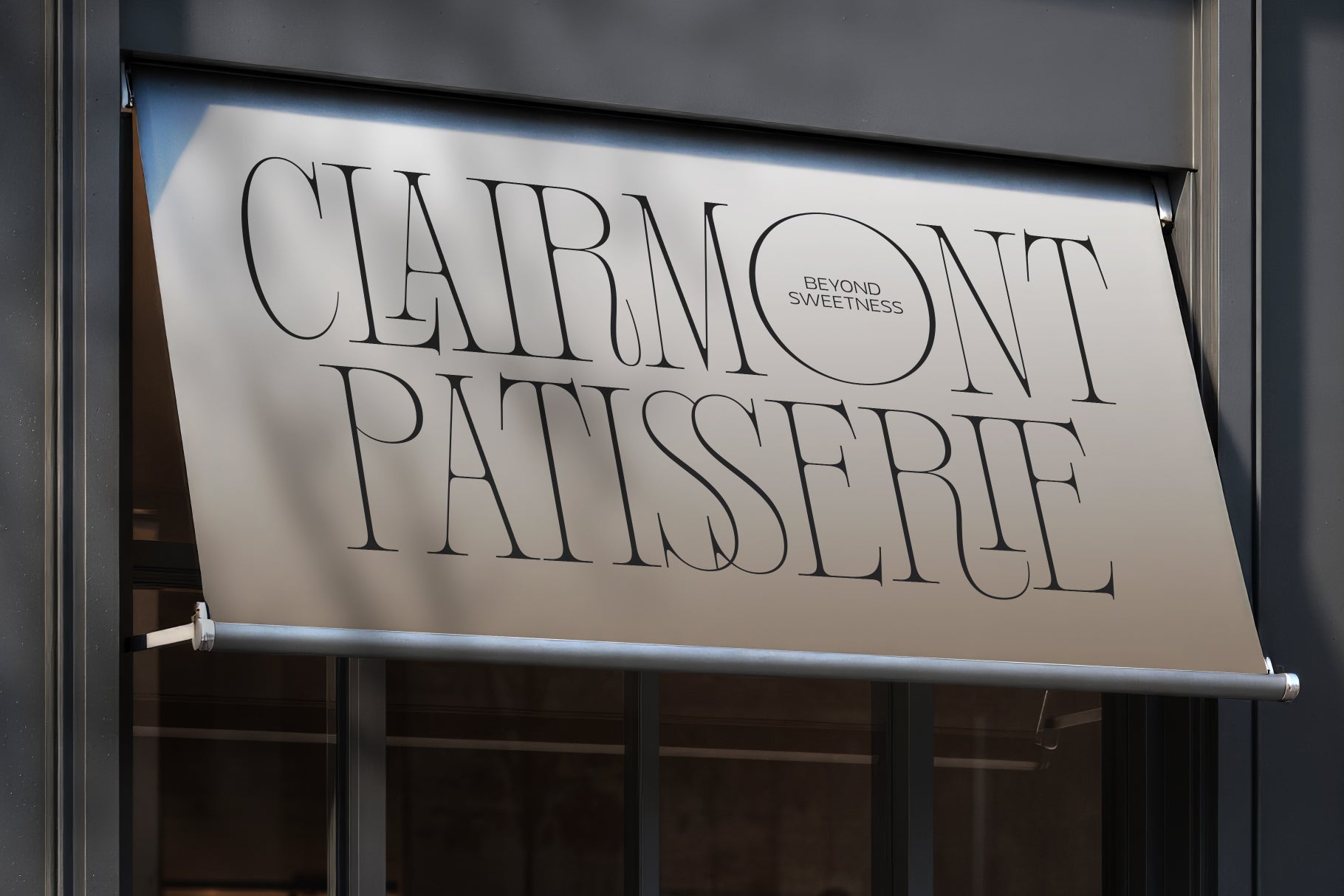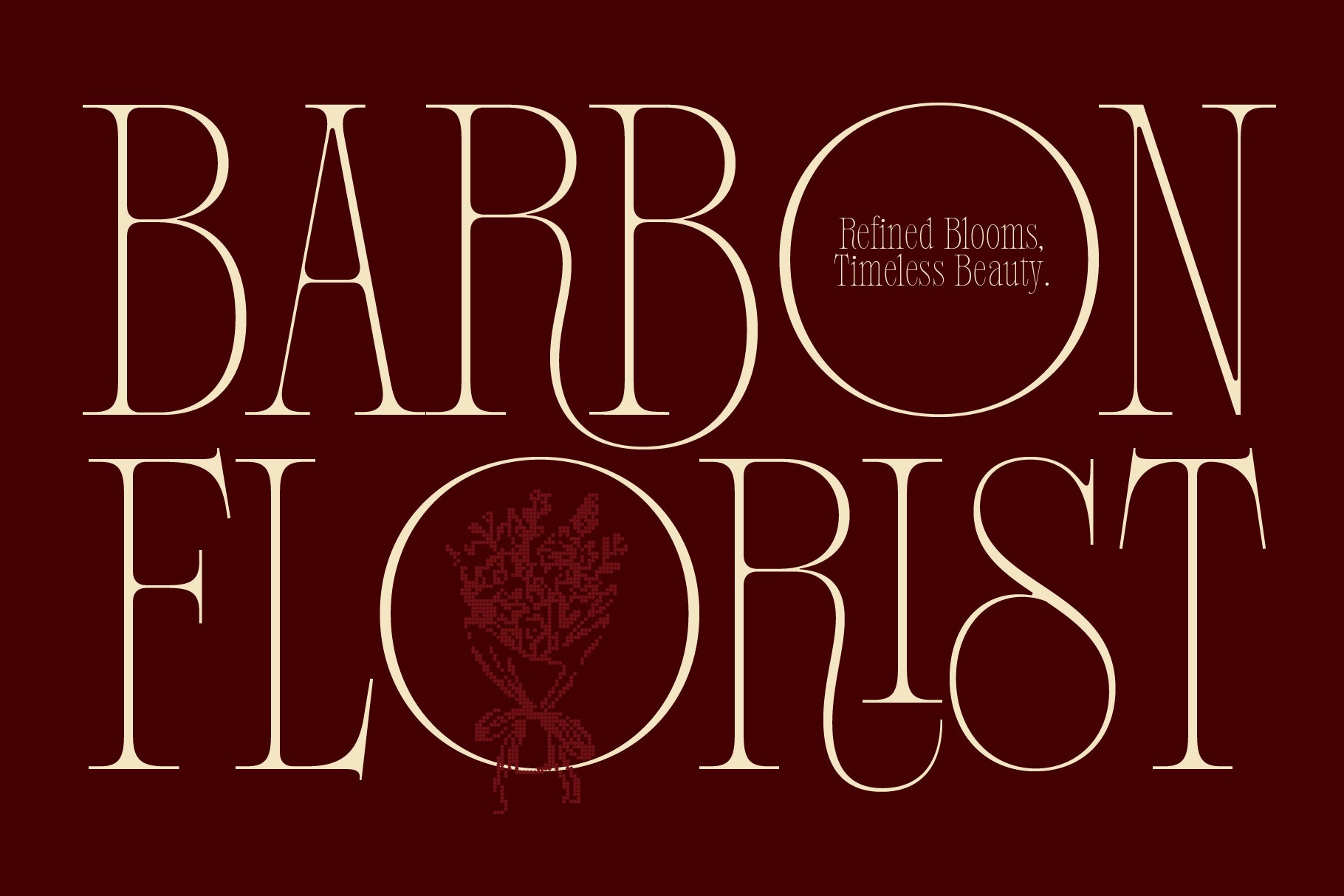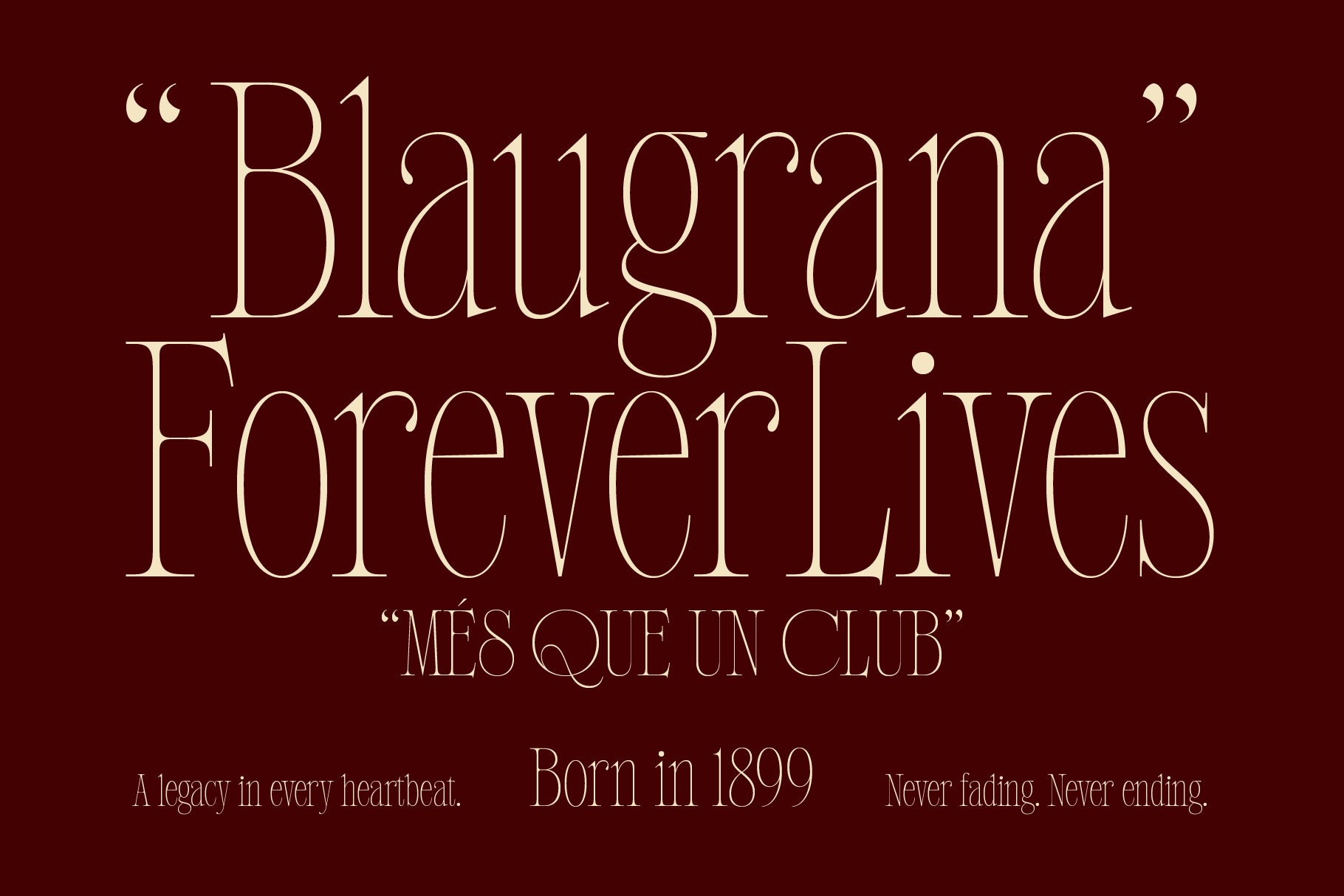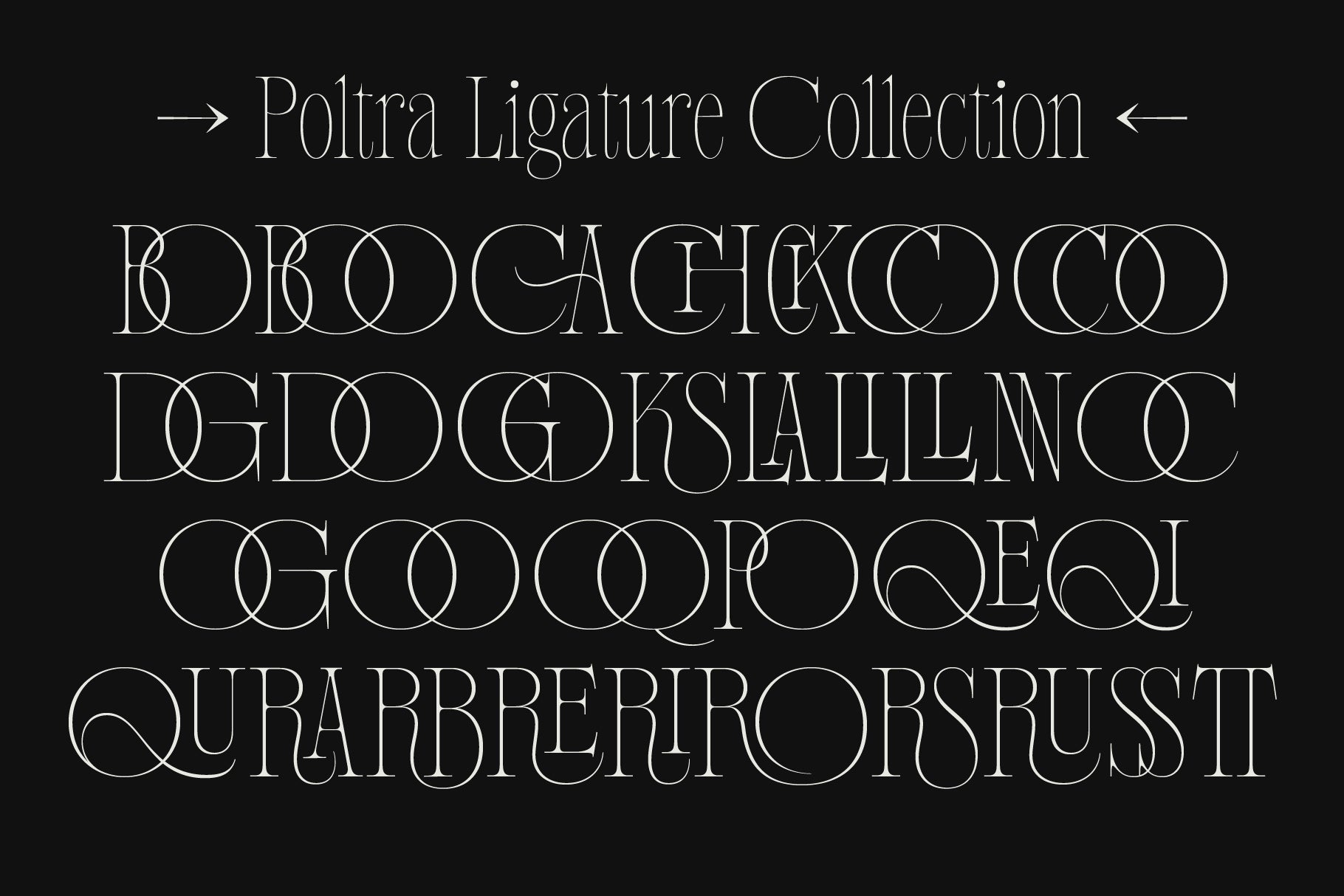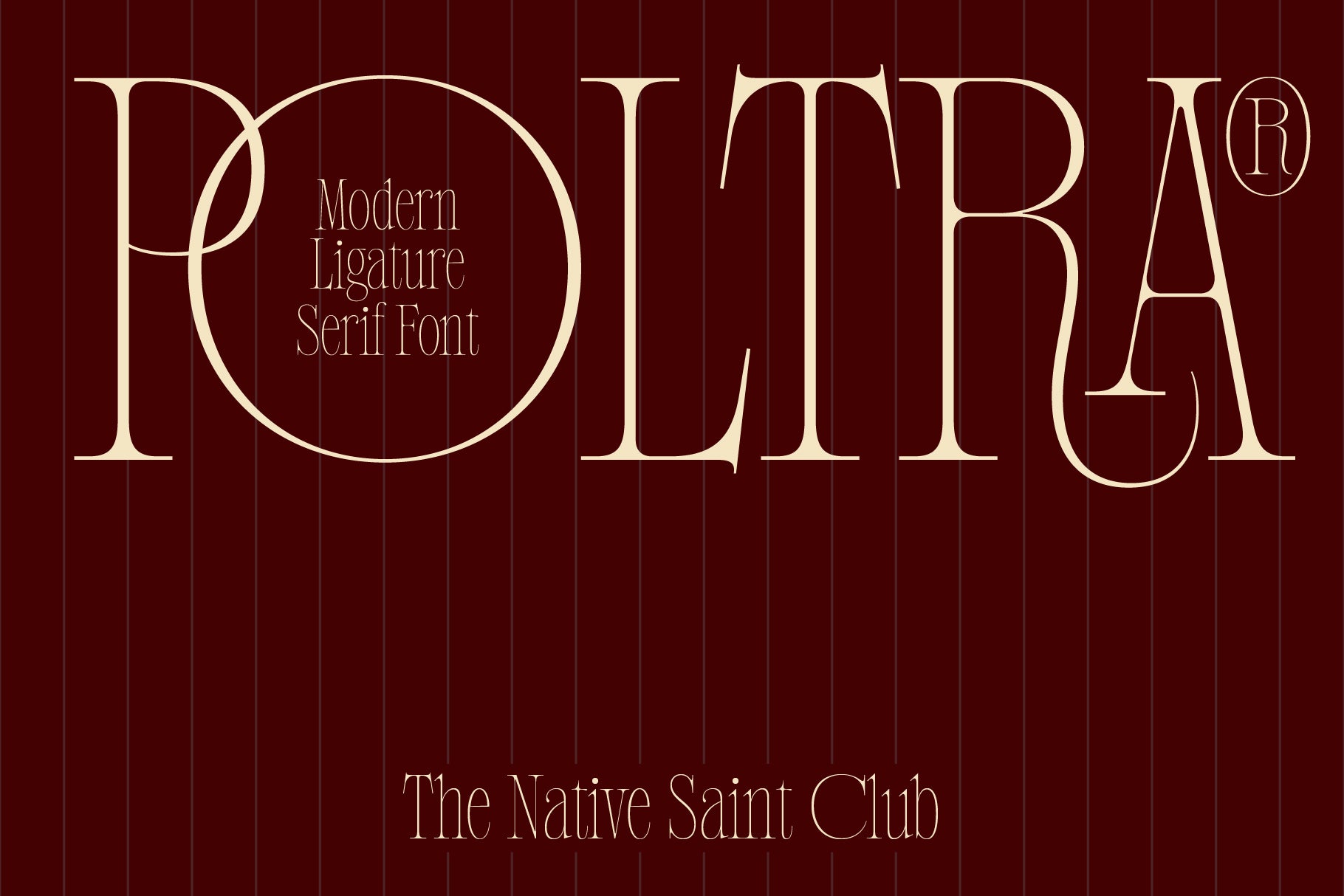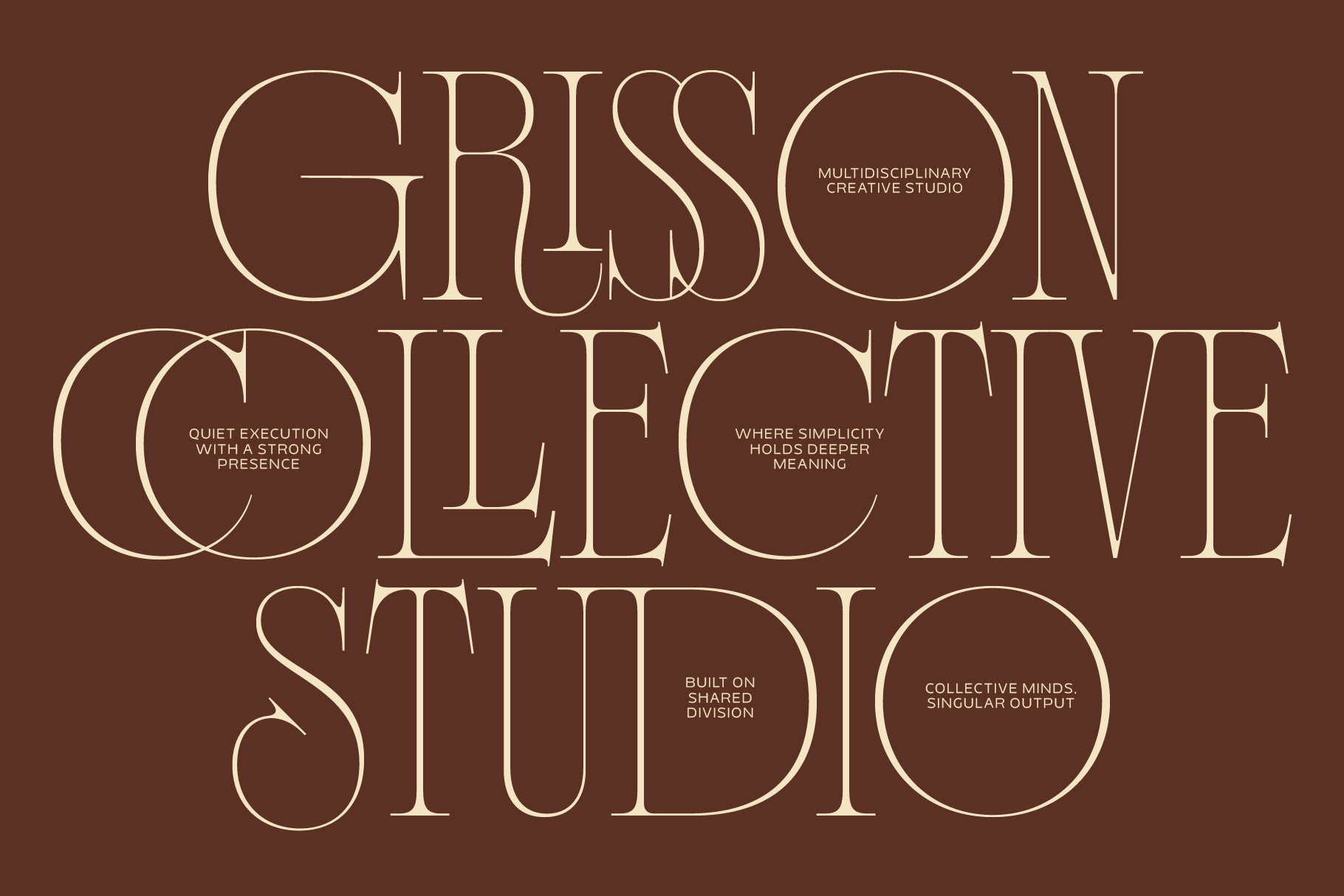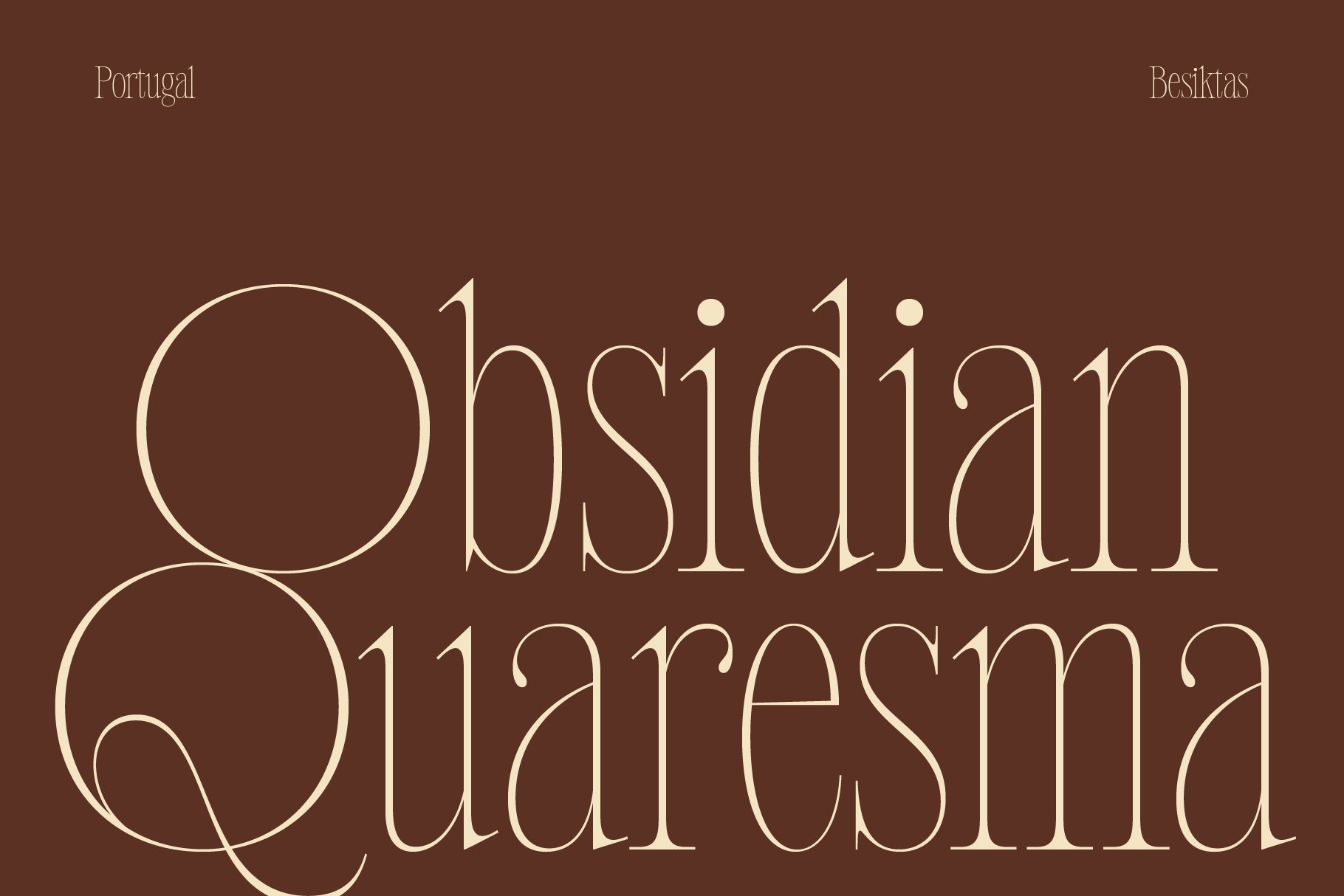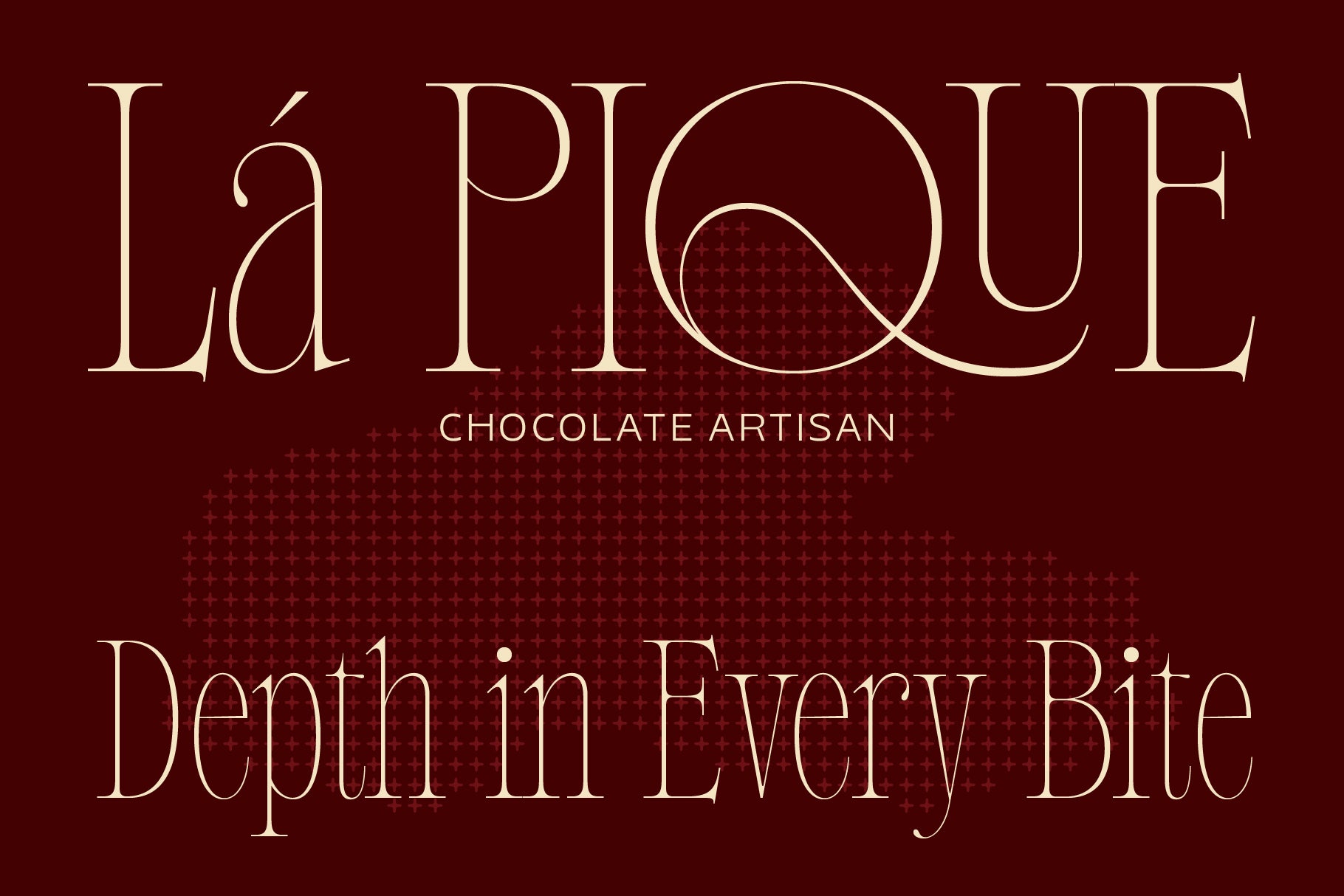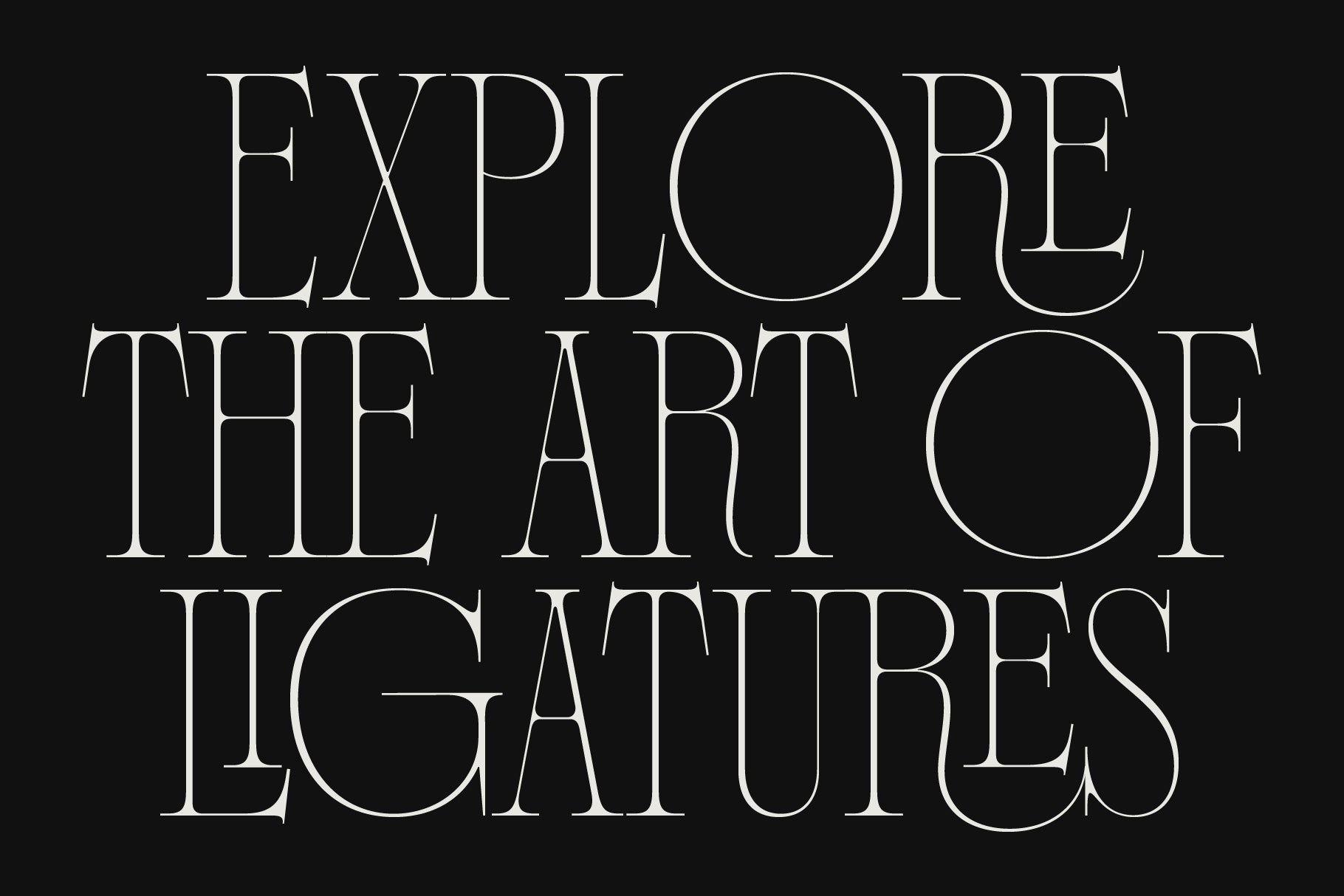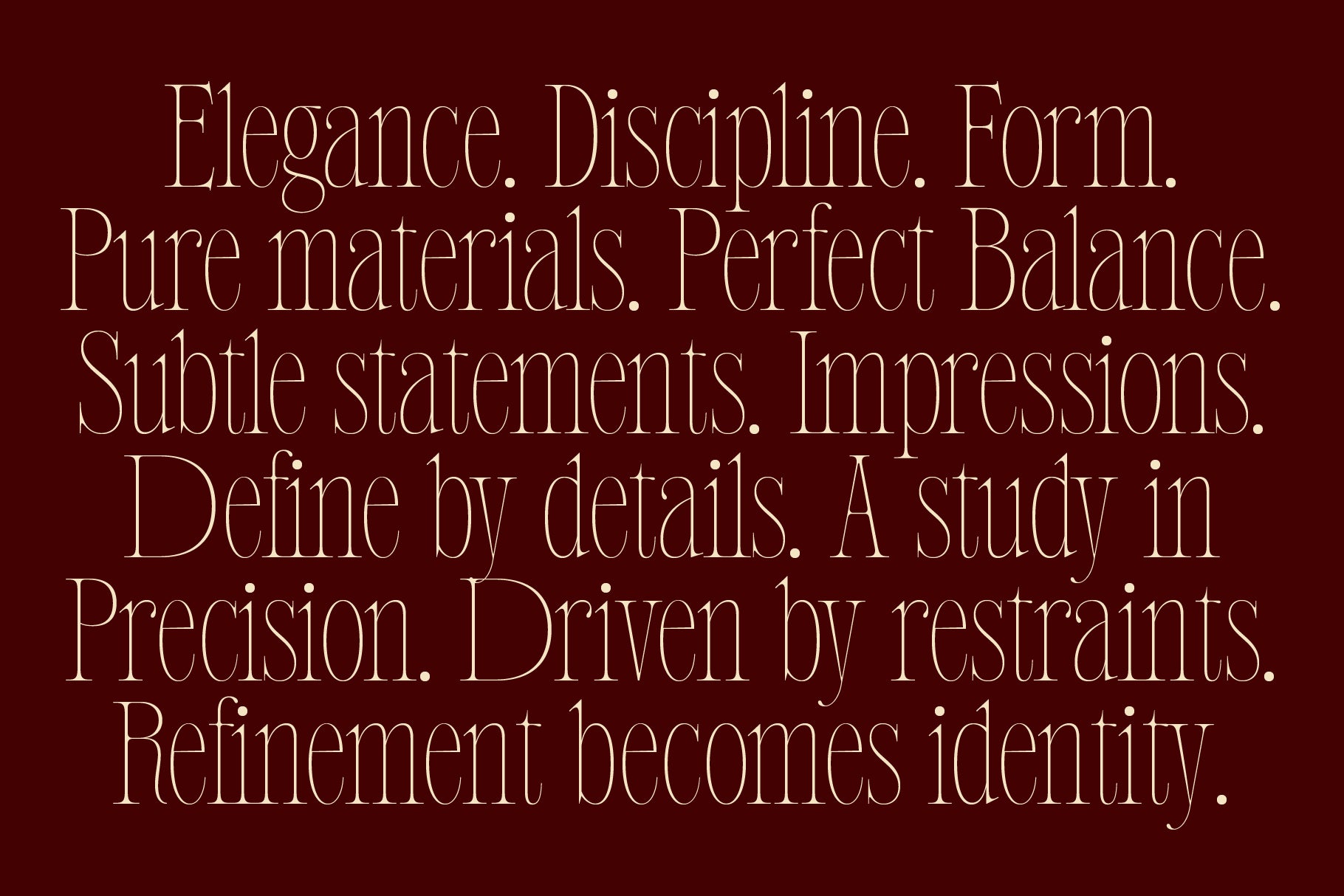
Tipografía Poltra TNSC
Poltra Typeface es una tipografía serif moderna con ligaduras, diseñada para aportar elegancia y personalidad a cada composición. Con sus elegantes formas de letra, trazos de alto contraste y ligaduras bellamente elaboradas, crea una voz visual sofisticada que resulta atemporal y contemporánea a la vez. Inspirada en la estética editorial, el branding de lujo y la tipografía expresiva. Creada para proyectos que buscan transmitir refinamiento, arte y originalidad. Funciona a la perfección para identidades de moda, empaques de boutiques, branding de restaurantes, menús de cafeterías, materiales visuales de hoteles, productos de belleza, portadas de libros, invitaciones, carteles y maquetaciones creativas de alta gama.
Cada curva y conexión de Poltra Typeface está diseñada para crear una sensación de ritmo, encanto y armonía visual. Las ligaduras aportan un carácter único que hace que los titulares y logotipos se perciban más exclusivos, mientras que la estructura serif mantiene un aspecto elegante y legible.
Características
• 689 glifos
• Minúsculas
• Mayúsculas
• Diacríticos
• Ligaduras
• Números
• Puntuación
• Símbolos
• Moneda
• Matemáticas
• Flechas